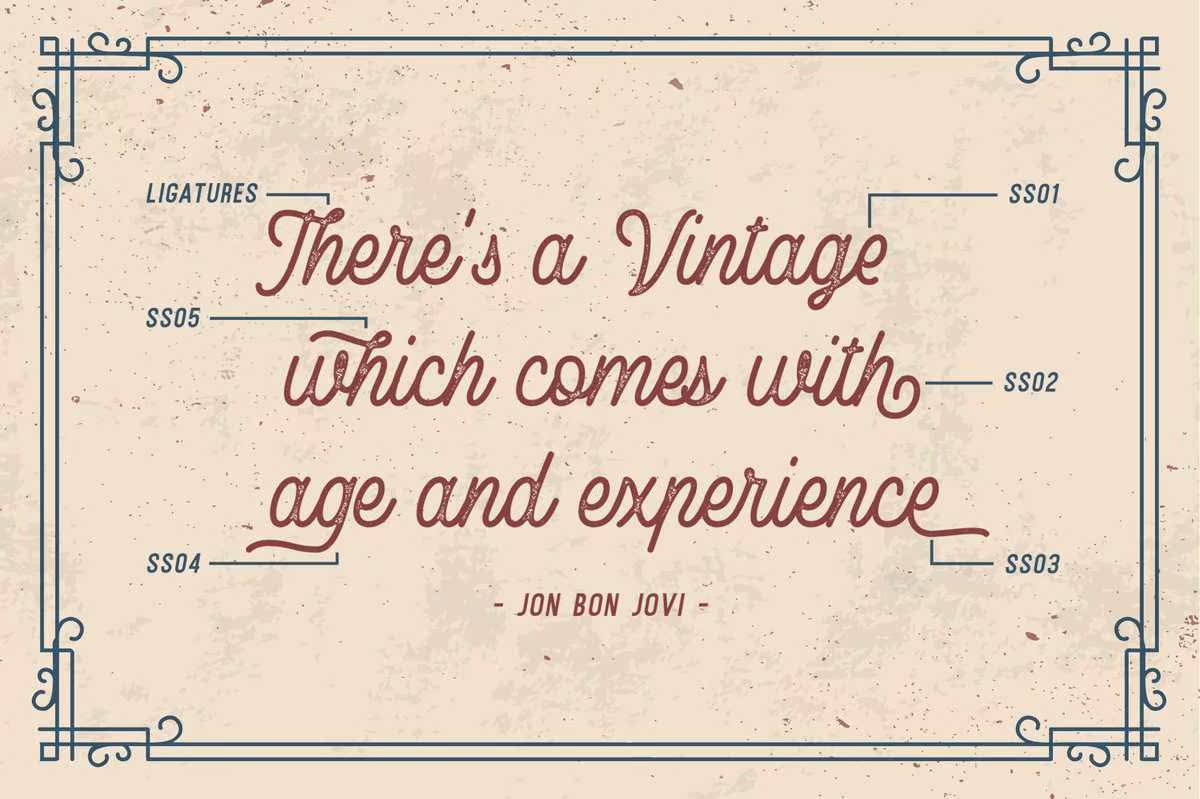
Runsell Studio呈现新产品差异之前,锈迹斑斑。我们制作了一个新的年份,包括13种字体:单线脚本、粗体脚本、sans和serifonts。每个字体都有2种样式:清洁和印花,可以支持您的年份样式。Runsell Studio呈现新产品差异之前,锈迹斑斑。我们制作了一个新的年份,包括13种字体:单线脚本,黑体字、sans和serifonts。每个字体上都有2种样式:Clean和Stamp,可以支持您的葡萄酒风格。